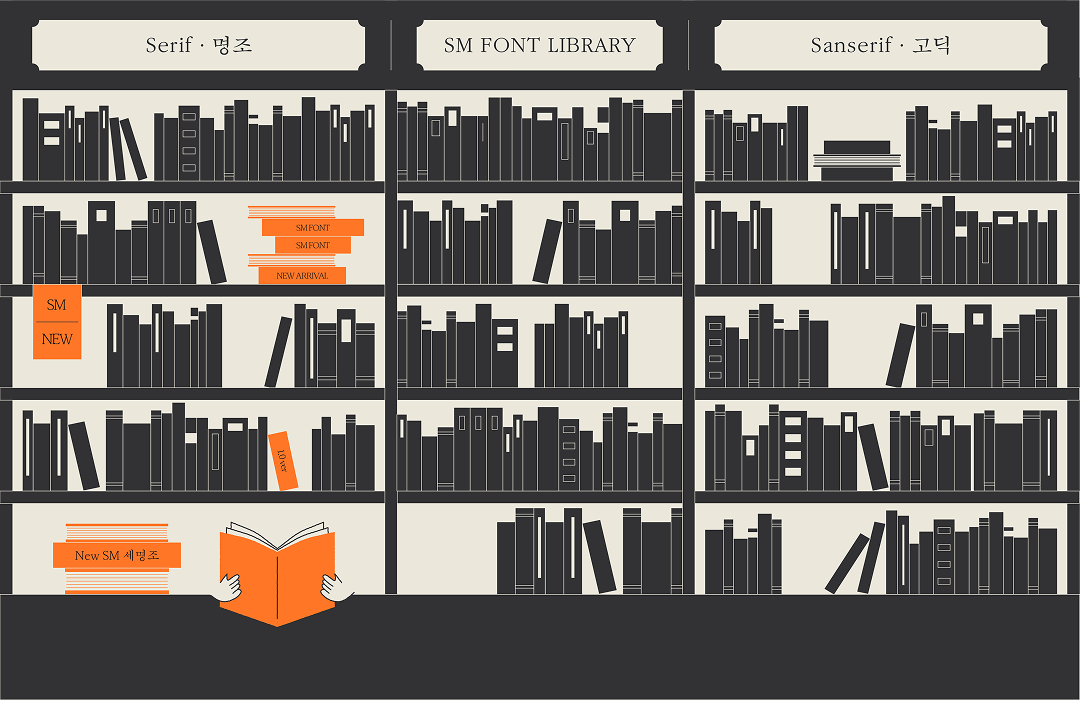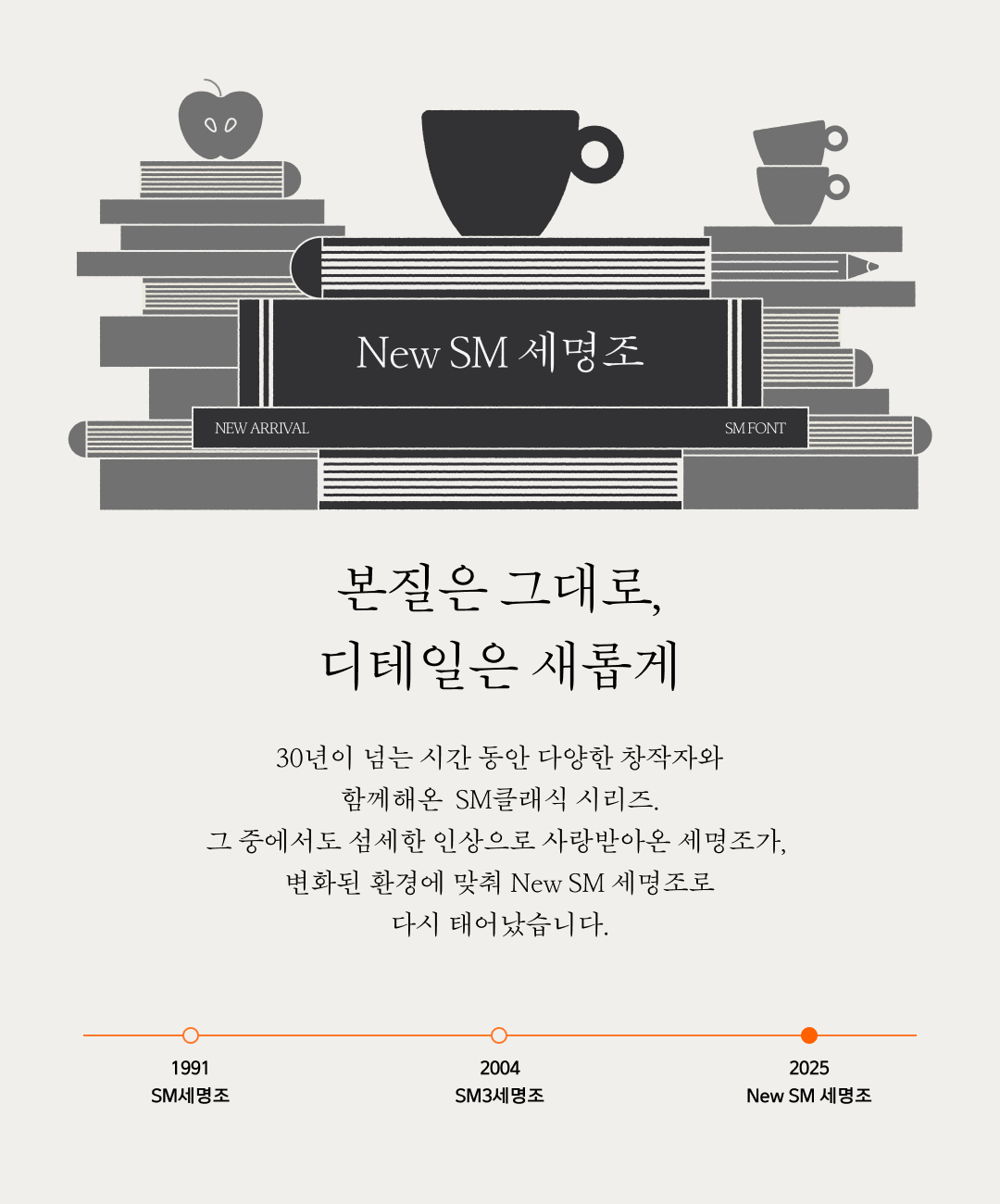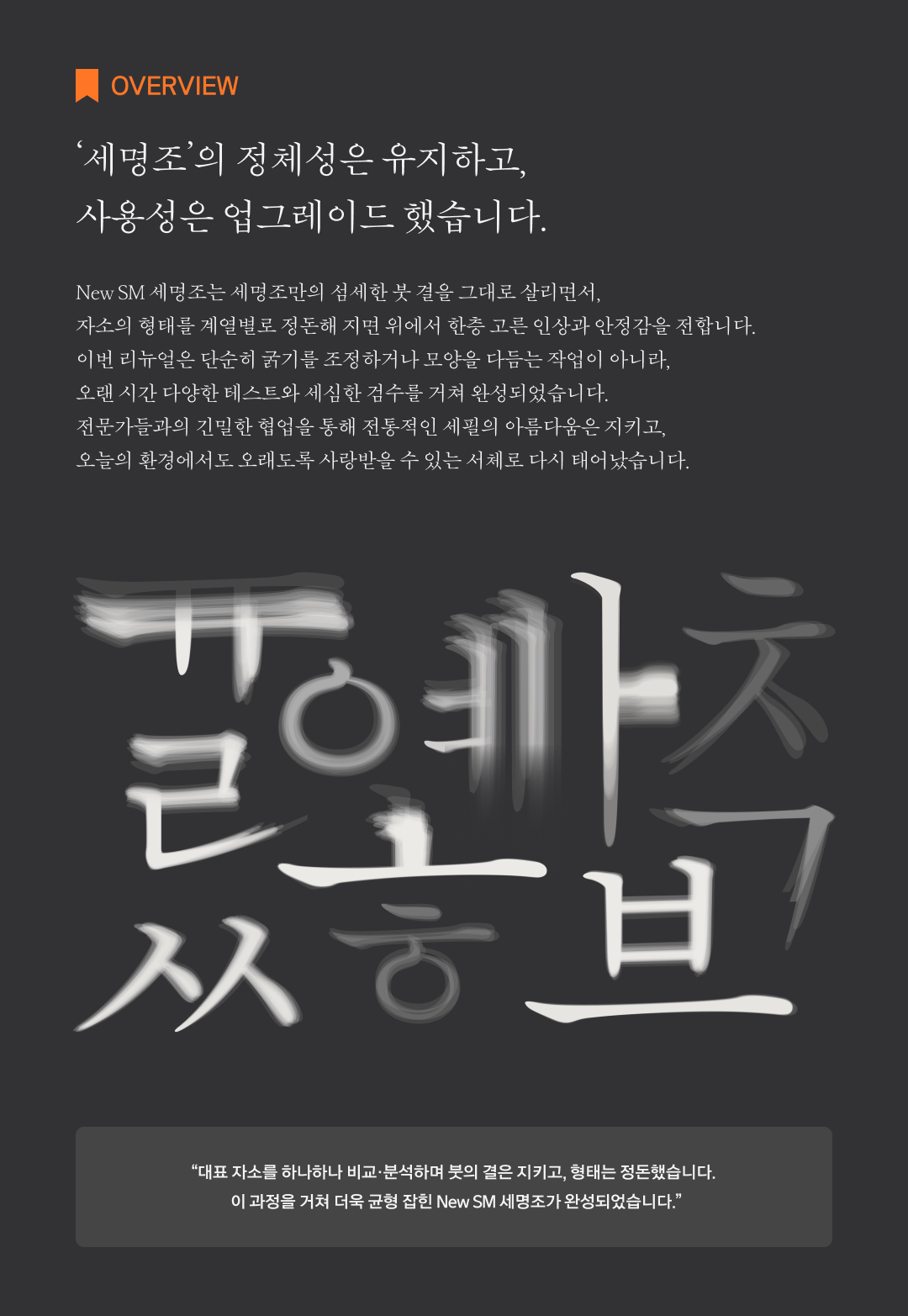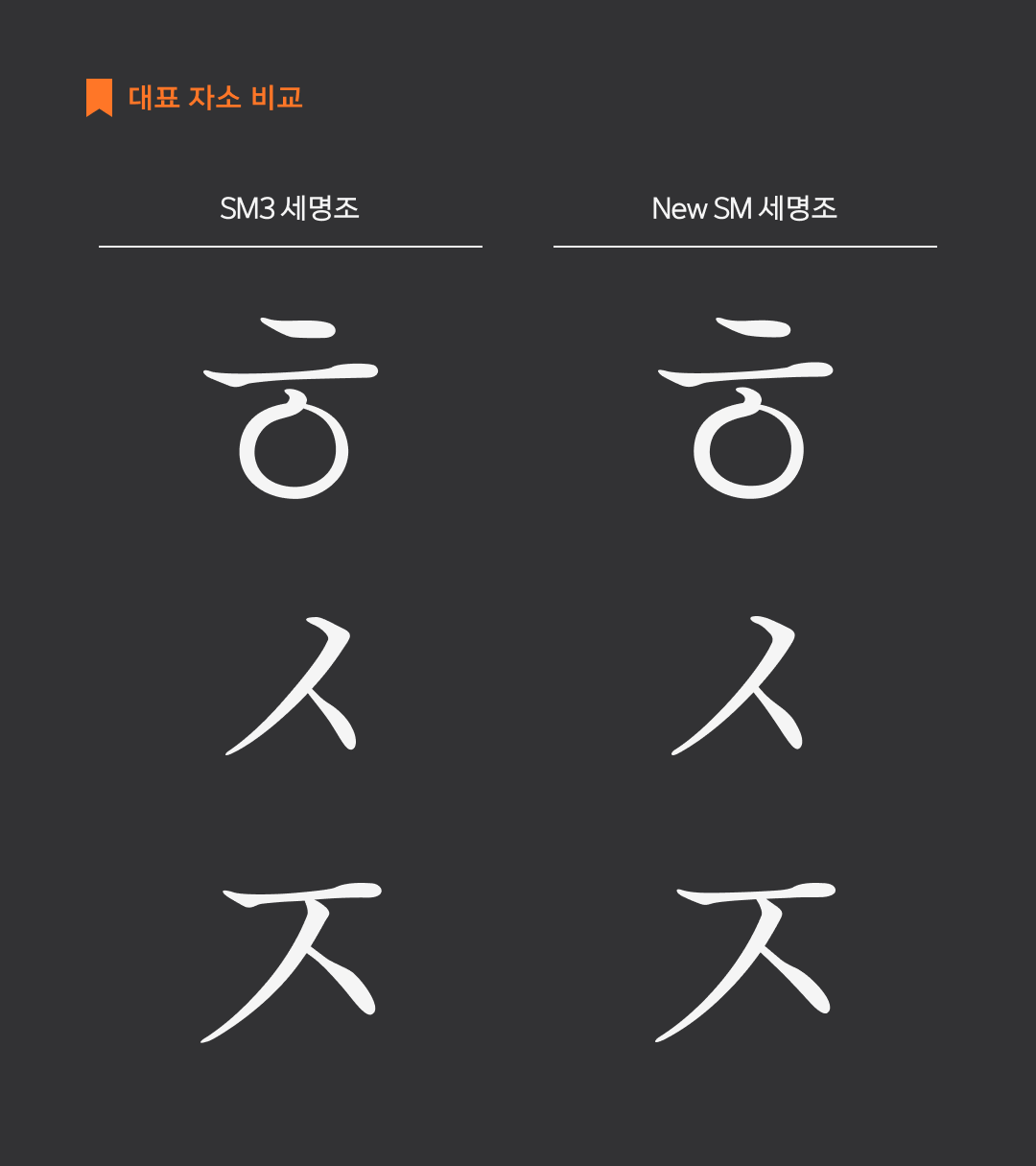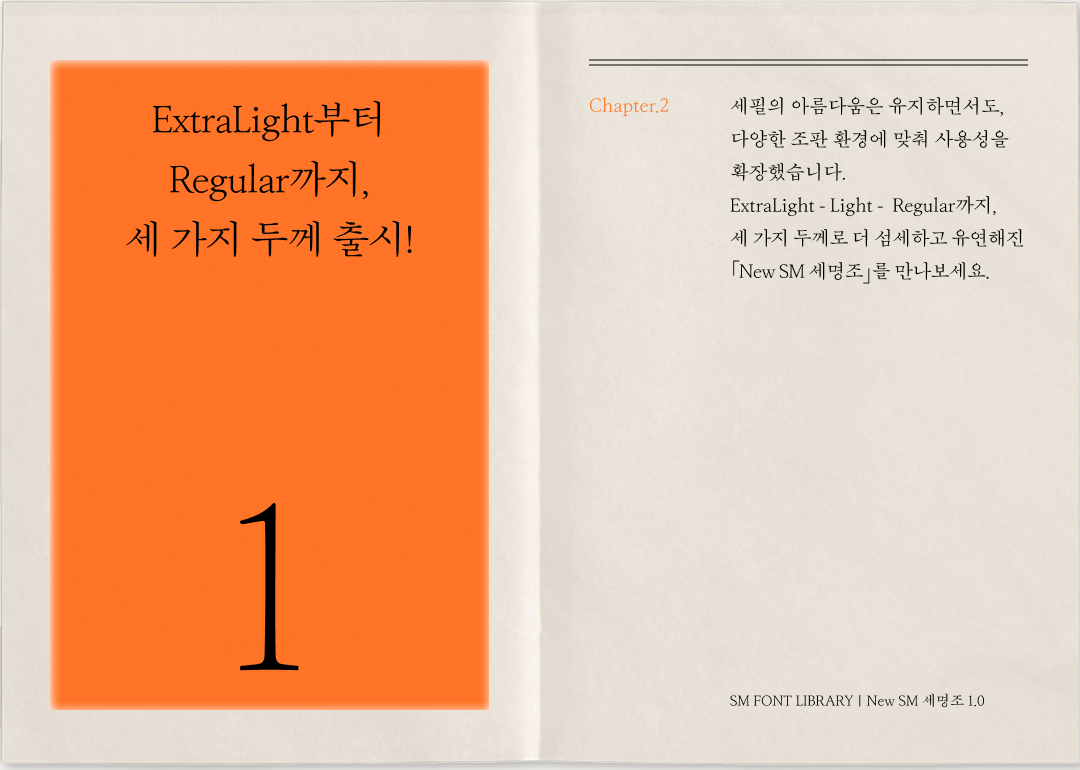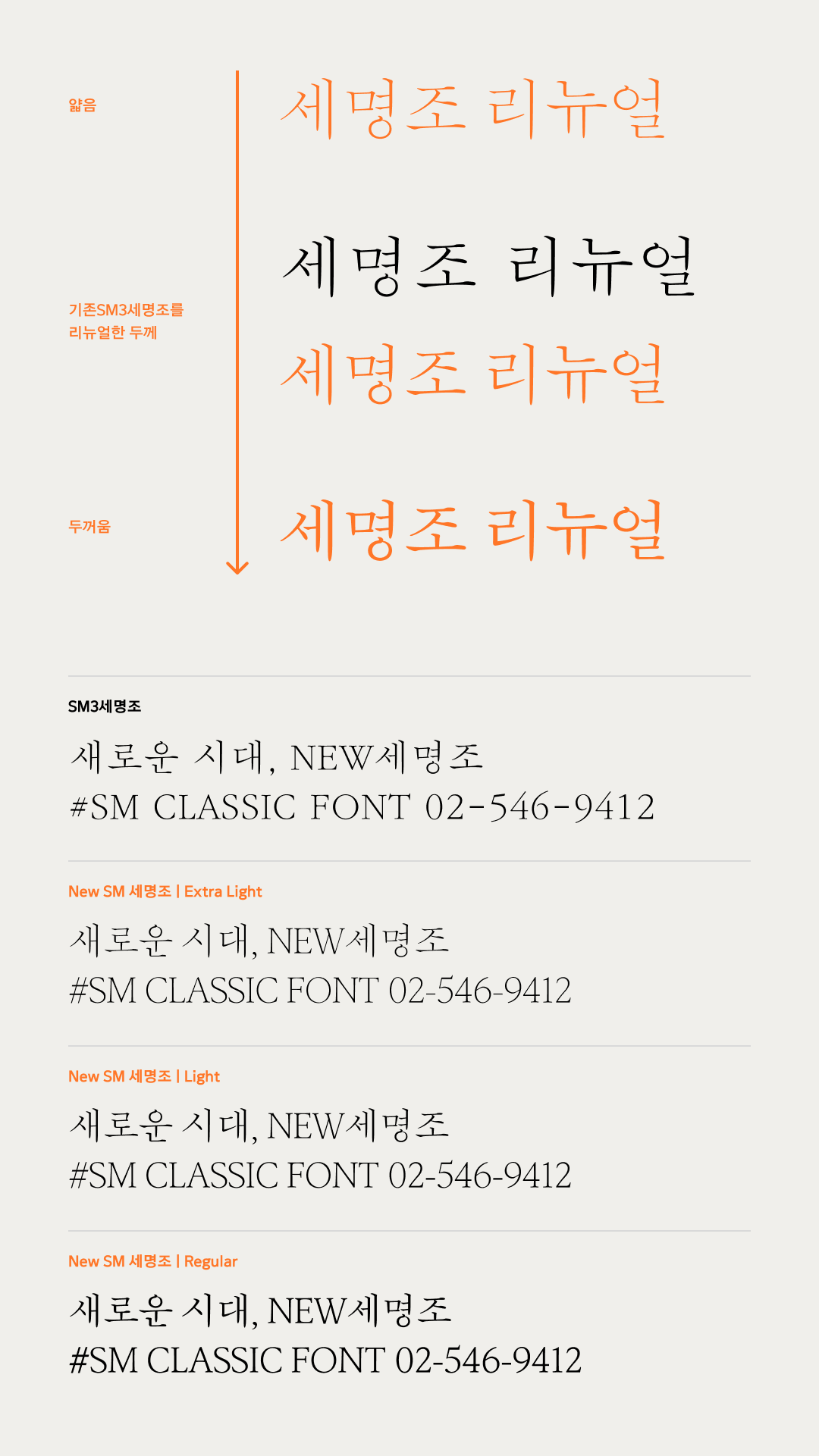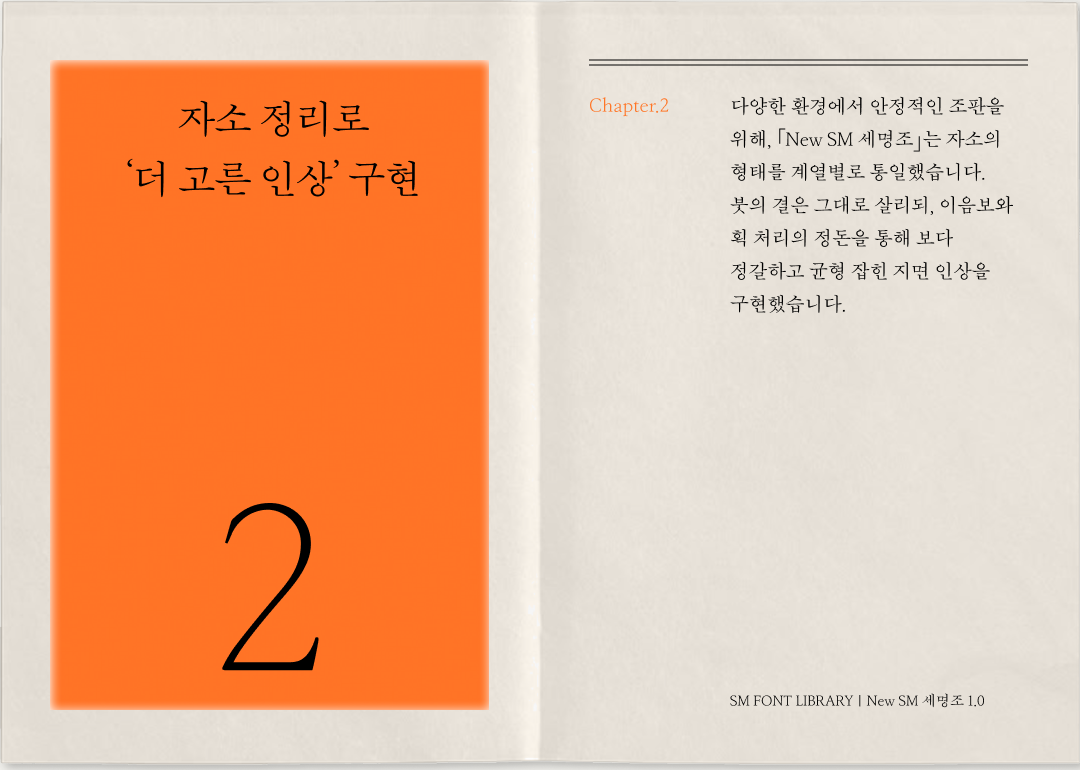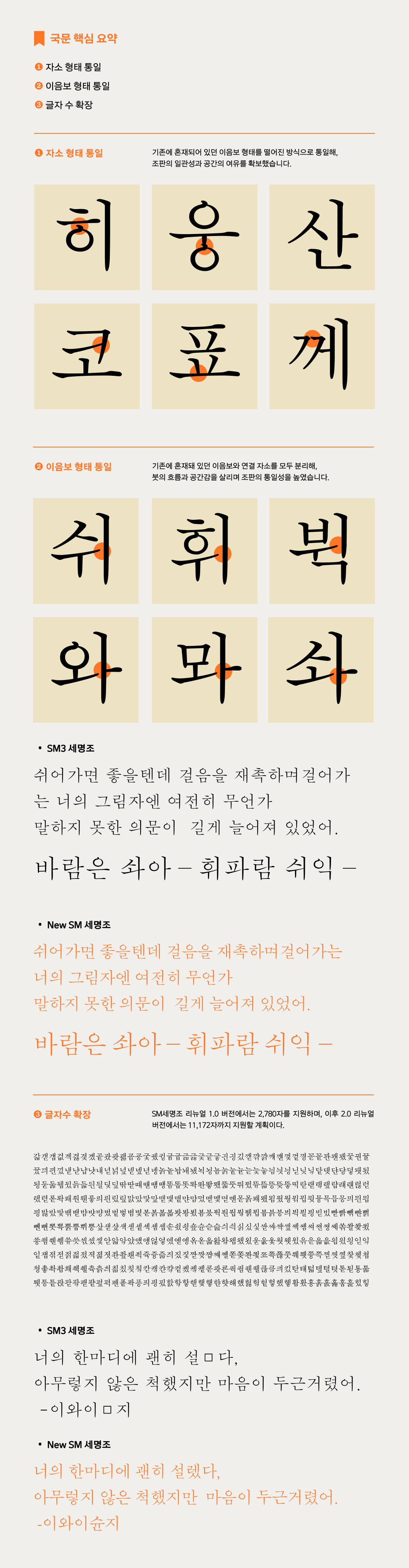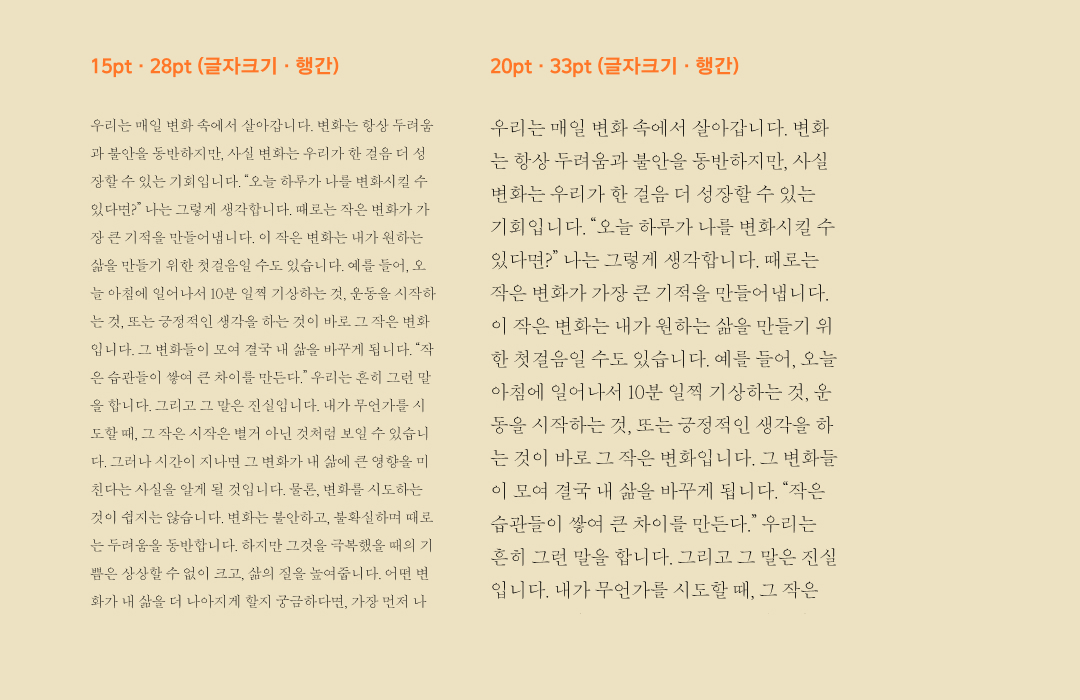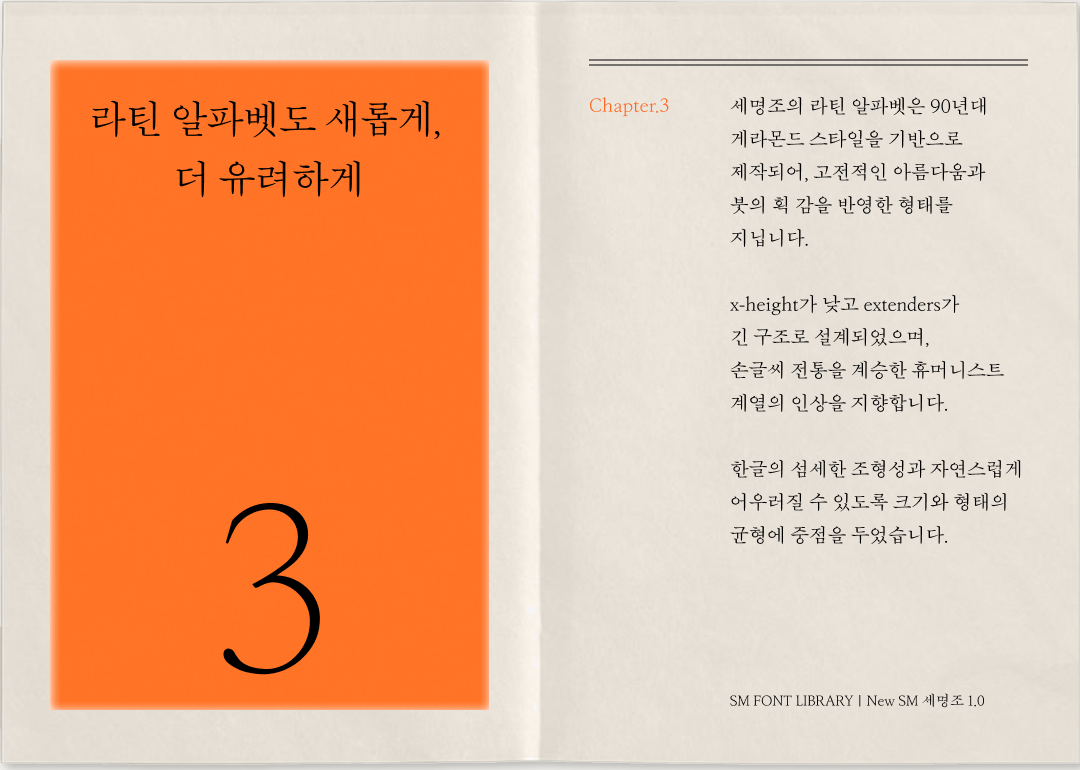
이번 1부에서는 세명조 리뉴얼의 핵심 변화와 과정을 함께 살펴봤습니다.
전통을 지키면서도 오늘의 환경에 맞게 다듬어진 여정을 확인할 수 있었죠.
이어질 2부에서는 New SM 세명조가 지면 위에서 어떻게 살아 숨 쉬는지,
다양한 조판 사례와 함께 그 매력을 더욱 생생하게 전해드리겠습니다.